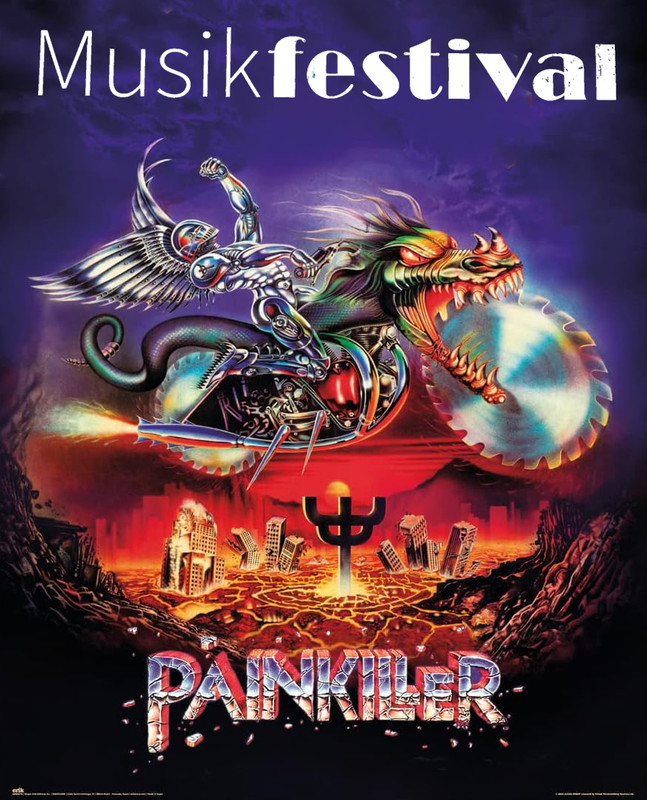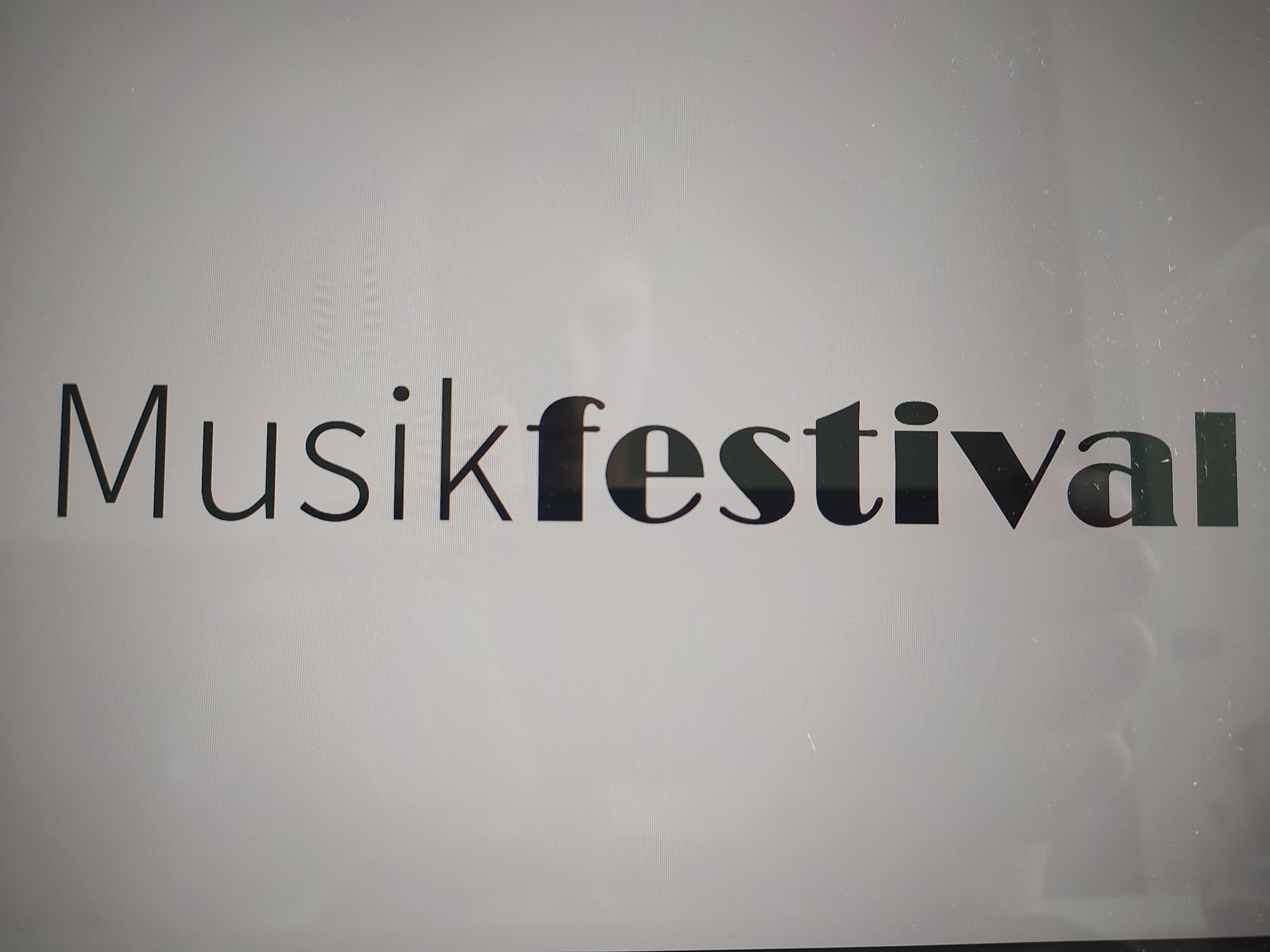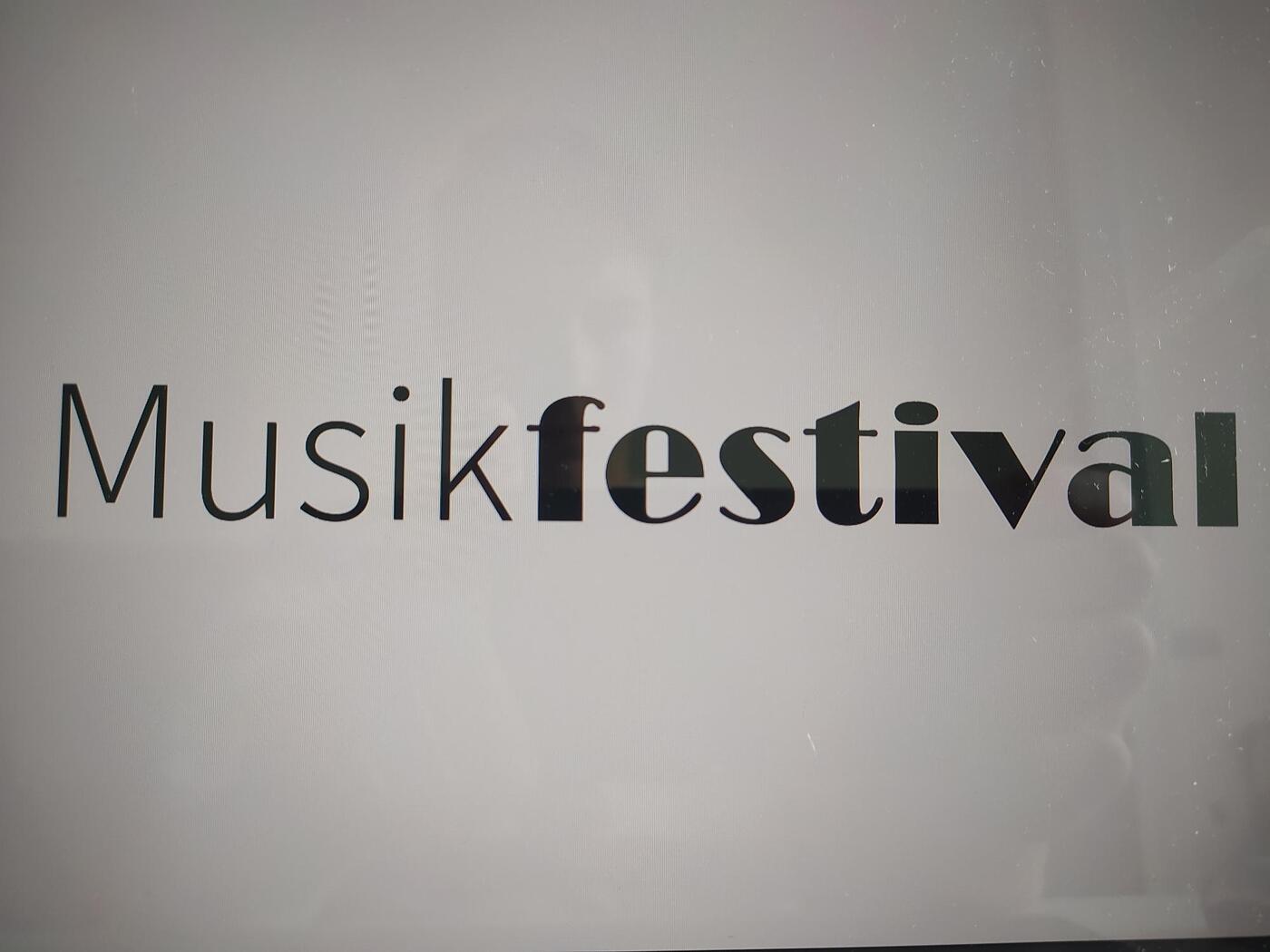
Schriftmischung zu "Musikfestival", was passt?
Hätte jemand gute Ideen und kann diese Argimentieren.
bitte zuerst um ein (einigermaßen) ausführliches briefing! (musikstil, zielgruppe, geografie etc). wacken ist nicht das selbe wie ein festival der volksmusik. :-?
es spielt keine rolle, die Stile sollten einzel zu den Wörter passen und dann typografisch korrekt abgestimmt sein.
hier gibt es viele hilfsbereite profi-gestalter aber wenn du keine näheren infos lieferst wird dir hier keiner weiterhelfen können. sorry to say!
Ich stehe eben auf dem Schlauch und habe keine Anhung, was sich kombinieren lässt. Ich dachte zuerst eine Handschrift mit einer Sans Serif zu kombinieren.
am besten du fängst hier an. wenn du das geklärt hast kannst du zum gestalterischen teil, der umsetzung gehen. den zweiten vor dem ersten schritt zu tun bringt nix.
ich habe nun mal eine gestaltung gemacht, vieleicht können sie mir eine rückmeldumg geben.
Klingt für mich alles erstmal nach einer Typo-Aufgabe für die (Fach-)Hochschule!? Deswegen auch keine genauen Angaben über die Musikrichtung etc. sondern nur das Wort bzw. die zwei Wörter Musik und Festival ... oder liege ich falsch :-?
In dem Fall wäre es nur fair, das auch dazu zu schreiben, dann weiß man worauf man sich einlässt und, ob man überhaupt die Übungaufgabe abnehmen will ;-)
Ansonsten würde ich so oder so sagen, probiere doch einfach mal aus und versuche selber zu argumentieren warum diese oder jene Schrift(Mischung) zu diesem oder jenem Stil passt.
Und wenn du gar keine Idee hast:
Das klingt (ohne nähere Infos) nach einer Hausaufgabe aus der GTA-Ausbildung. Falls es so ist, hast du mehr davon, wenn du deine eigenen guten Ideen und Argumente dafür findest.
Wenn du für den Einstieg an die Hand genommen werden möchtest, probier es mit Erik Spiekermanns kostenlosem Buch »Stop Stealing Sheep«.
Du kannst darin mit dem Quiz auf Seite 42 starten, um zu verstehen, worum es bei der Schriftauswahl geht und dass es hier nicht binär »richtig« und »falsch« gibt, sondern eher etwas im Sinne einer langen Skala von »passend« bis »unpassend«.
Inspiration für die Argumentation von schriftbezogenen Assoziationen findest du auf S. 61—73 (im Sinne von Outfits) und auf S. 121—129 geht es sogar konkret um Musik. Die Musikmetapher findet sich aber überall im Buch wieder. Typografie hat eben viel mit Rhythmus, Stimme und Lautstärke zu tun.